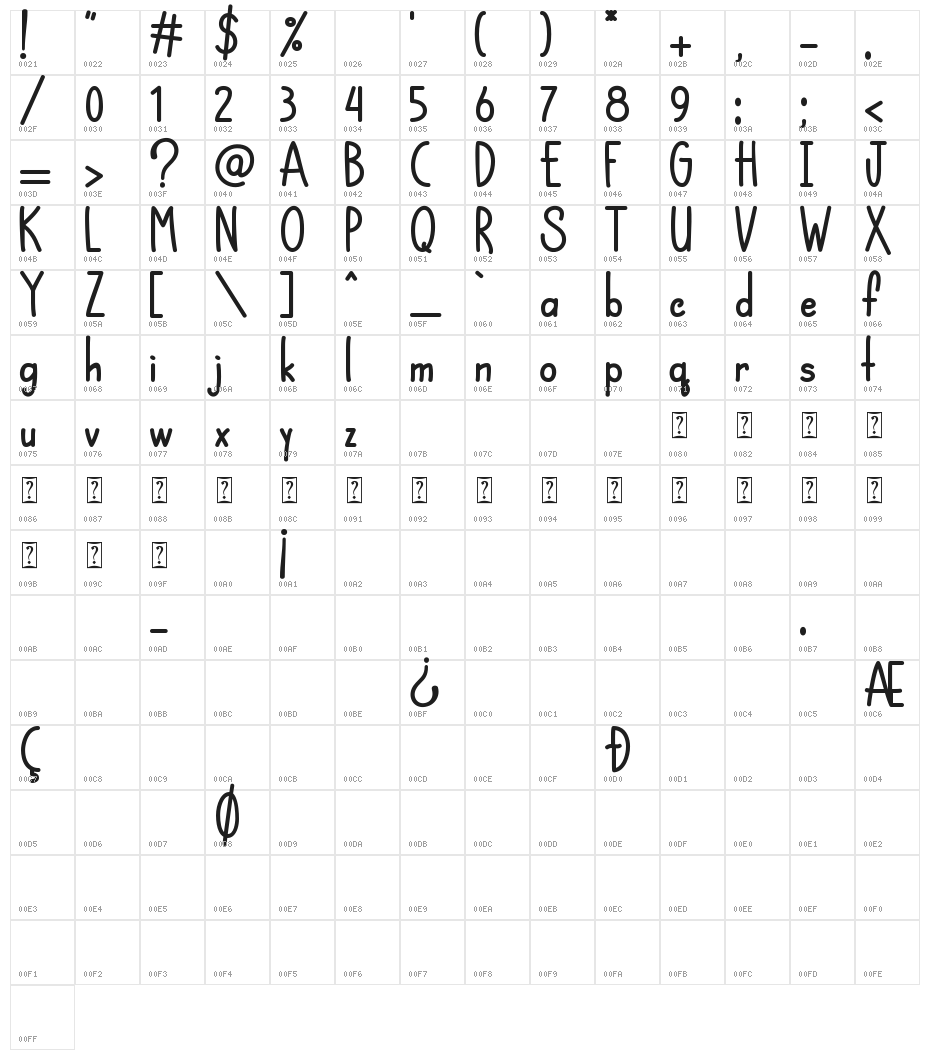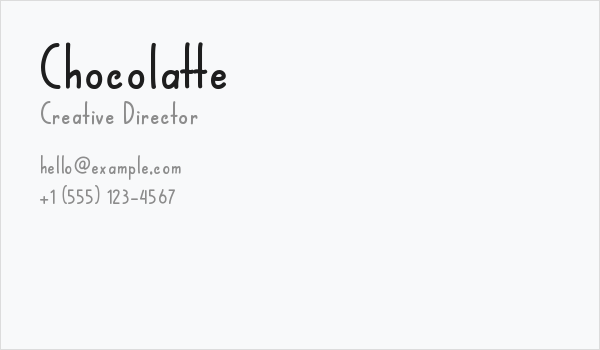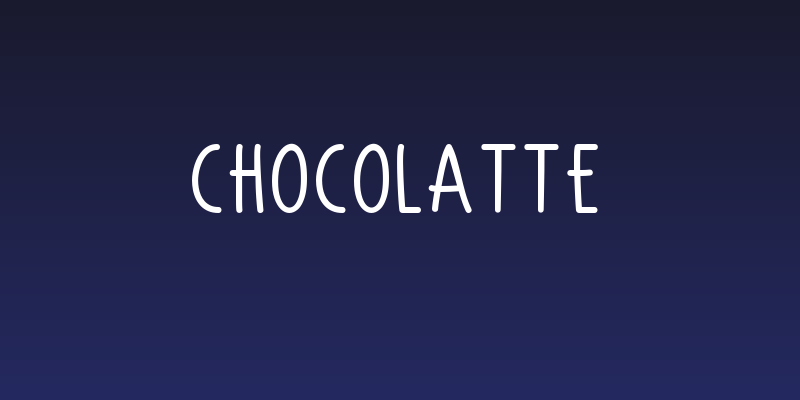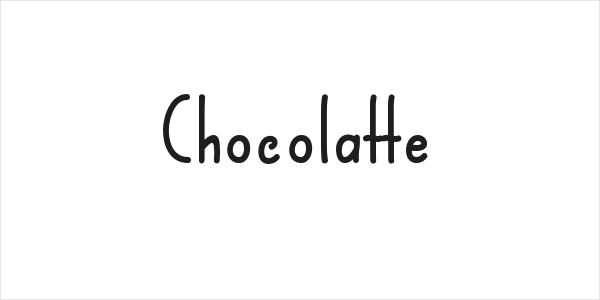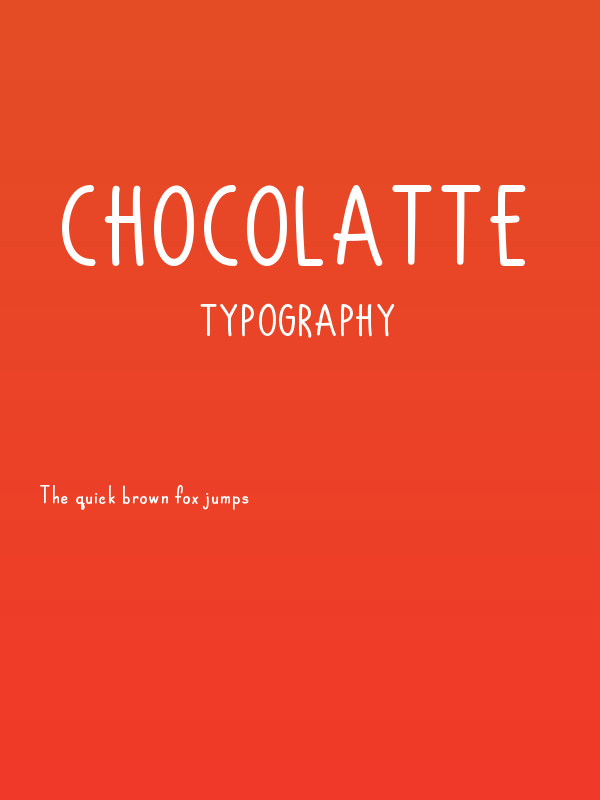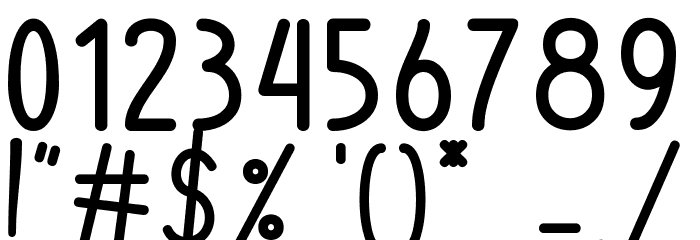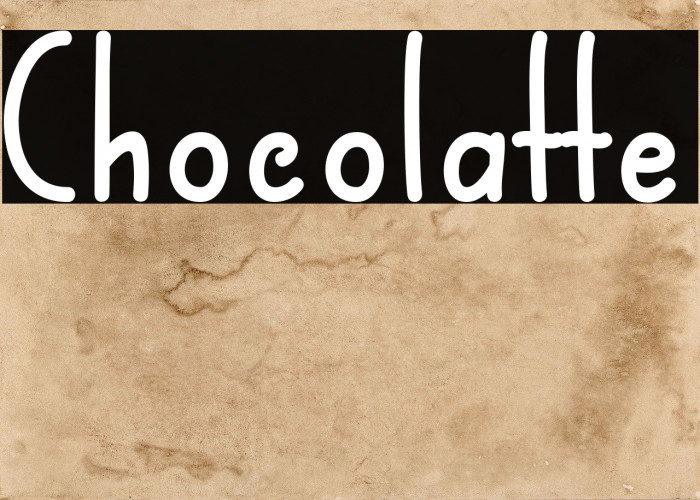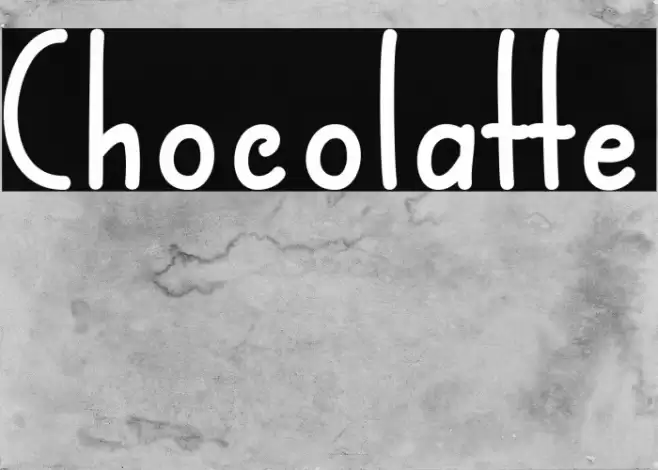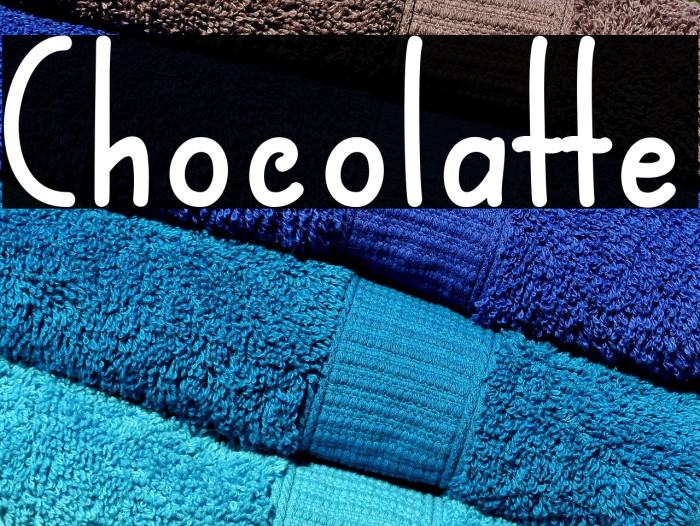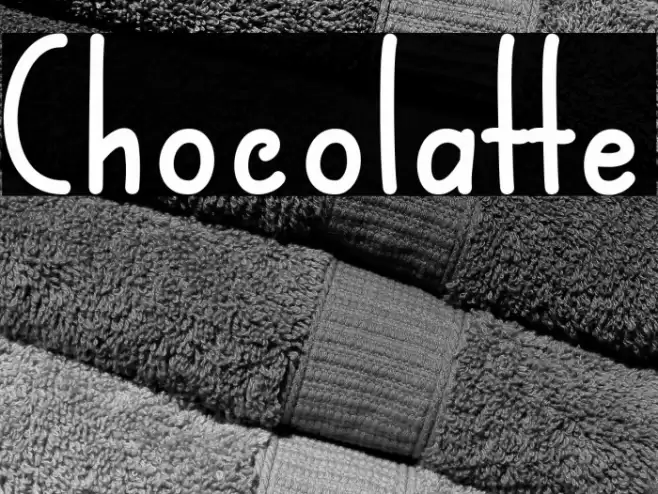
Chocolatte Font
| Gesamtstil | Casual |
| Anwendungsfall | Headlines, Logos, Informal Text |
| Vorgeschlagene Projekte | Ideal for children's books, greeting cards, playful branding, and social media graphics. |